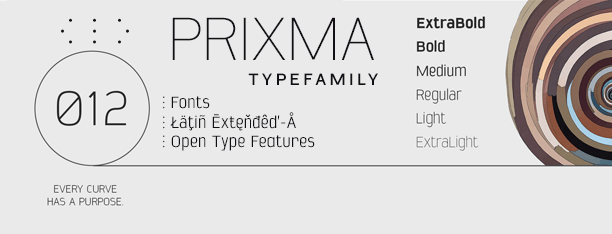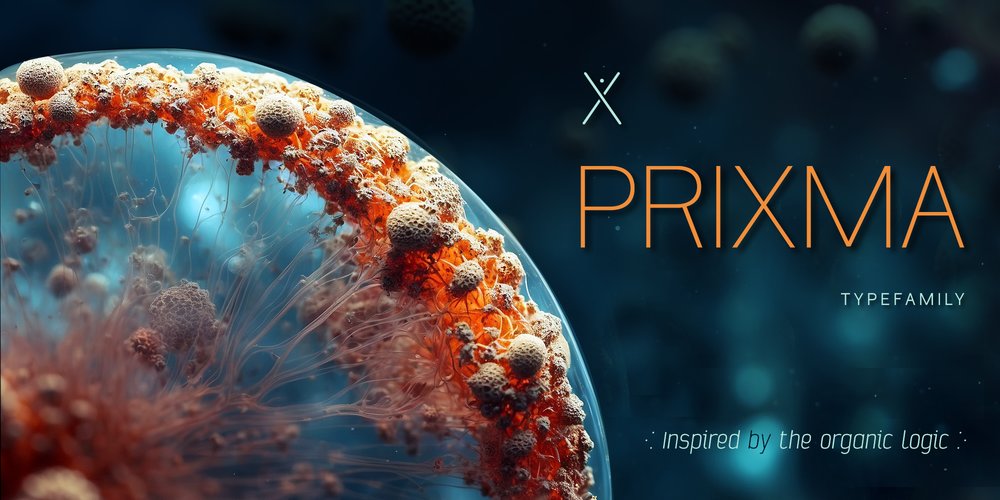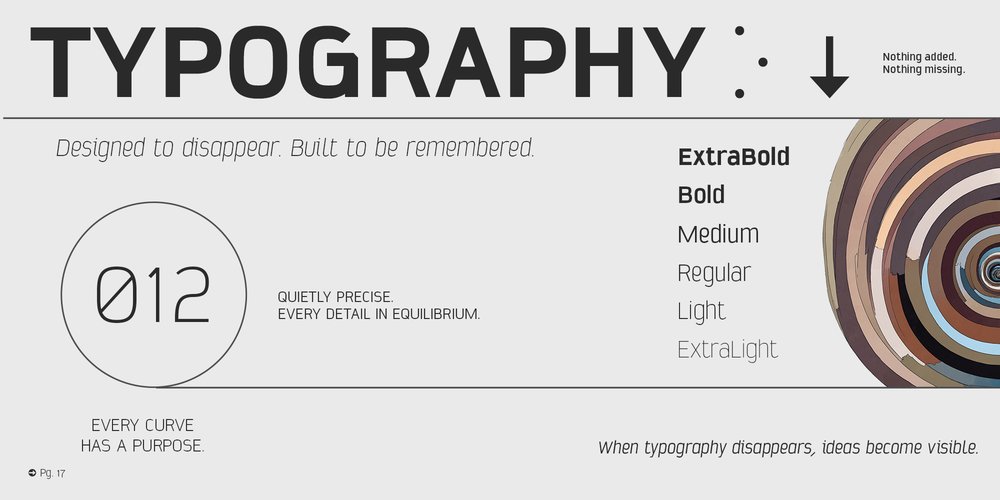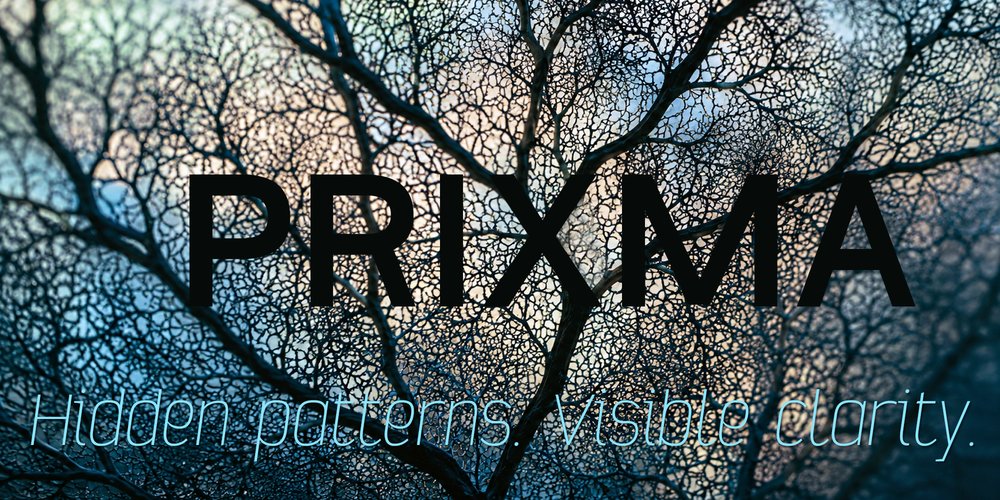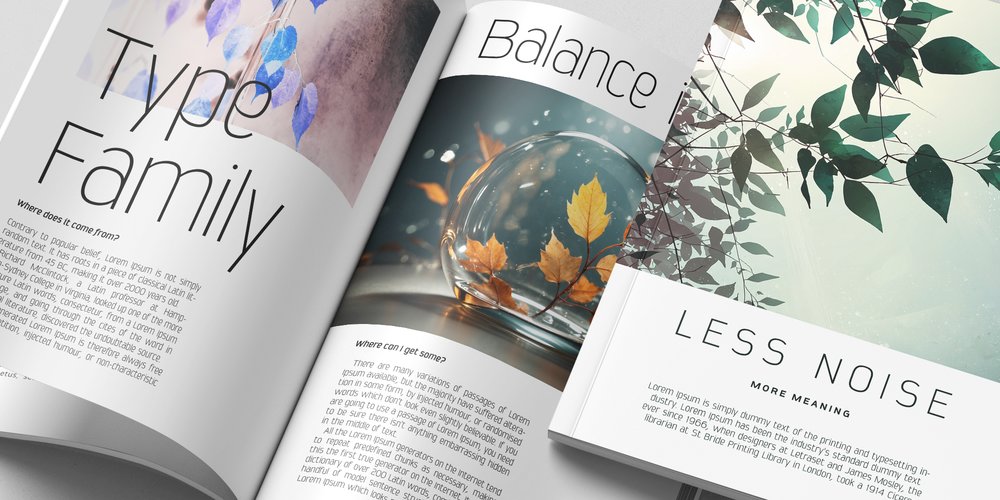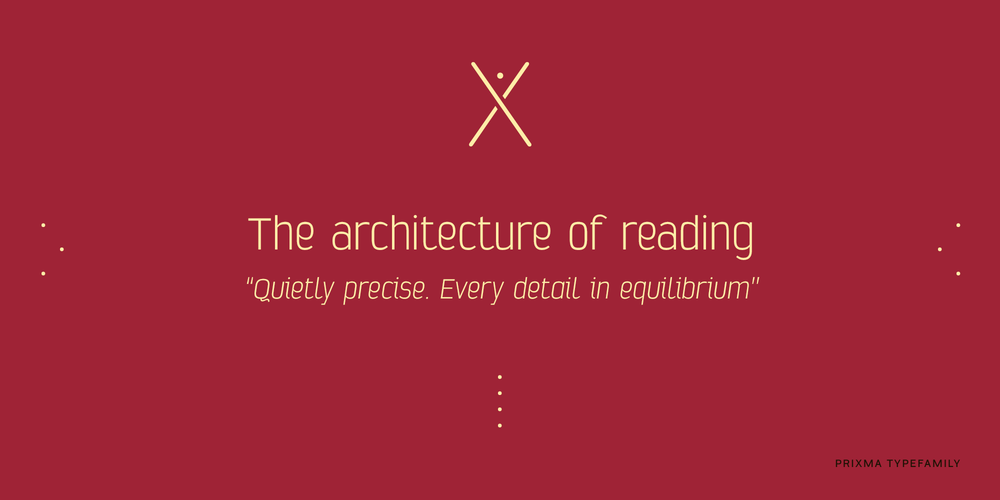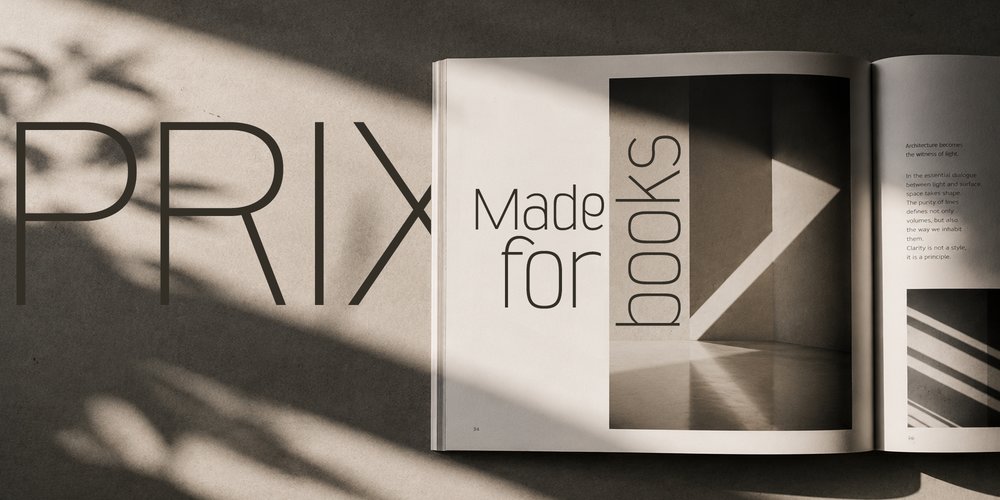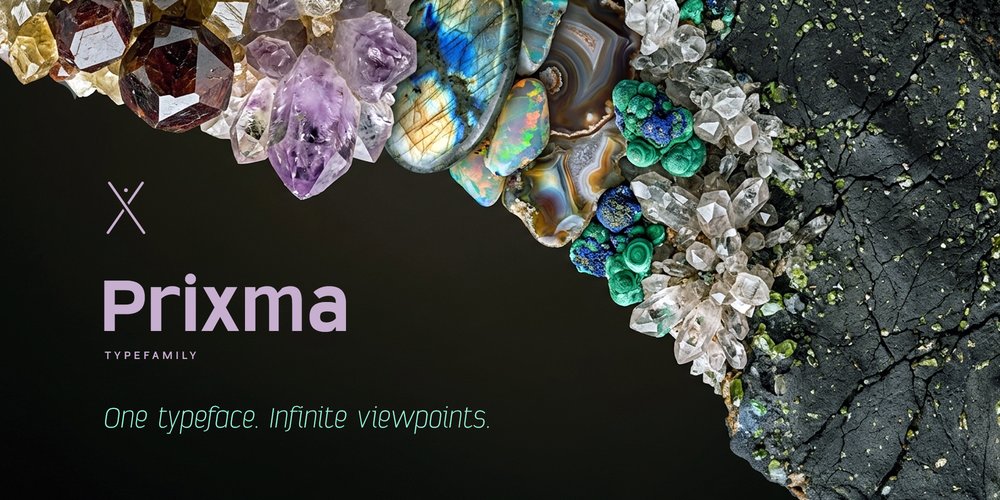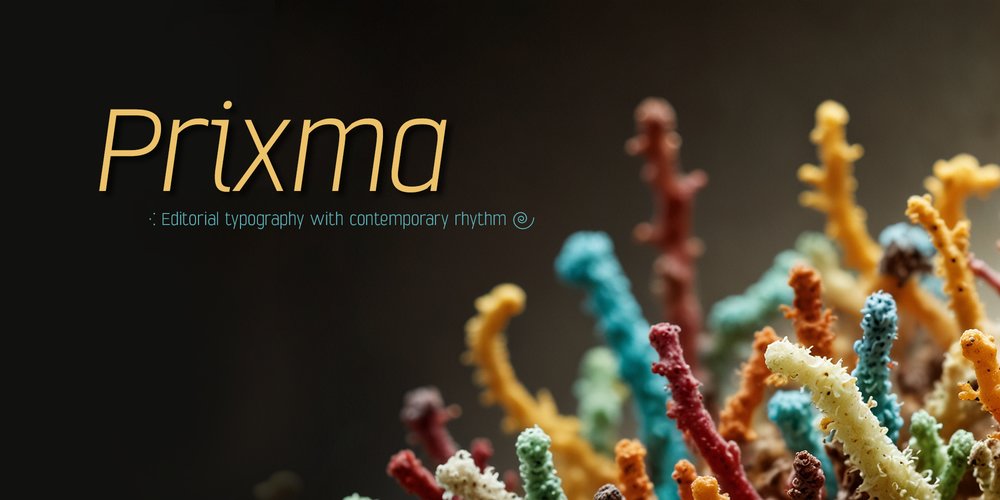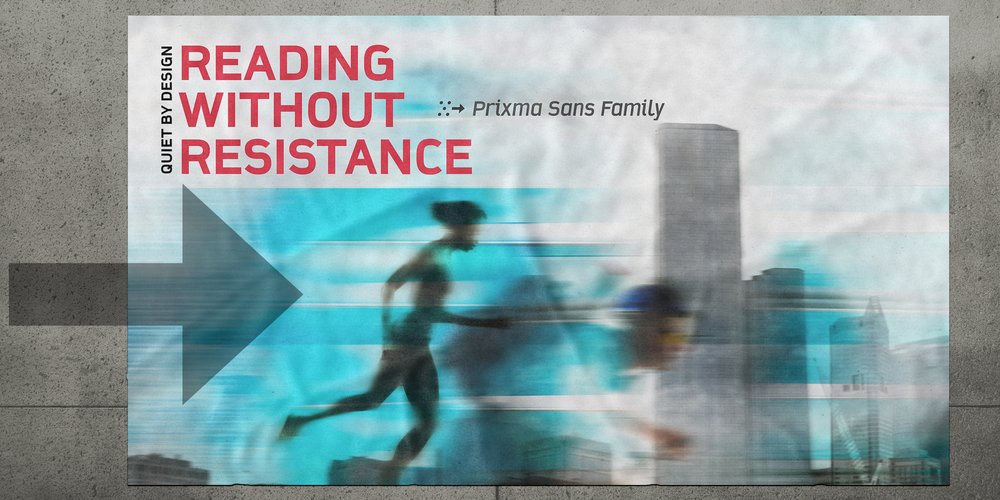
Estilo: Sans Serif, Editorial, Branding, Display, Packaging
Proporción: Extra Light, Light, Regular, Medium, Bold, Extra Bold
Alternates: 235
Latin-Extended: Latín Básico, Europa Occidental, Central & Oriental.
Funciones OpenType: Additional languages, All Alternates, Alternate Annotation Forms, Bitcoin, Capital Spacing, Contextual Alternates, Denominators, Discretionary Ligatures, Fractions, Historical Forms, Inferiors, Kerning, Localized Forms, Numerators, Oldstyle Figures, Optical Size, Ordinals, Scientific Inferiors, Slashed Zero, Standard Ligatures, Stylistic Set, Subscript, Superior letters, Superiors, Superscript.
Regular & Italic | 12 editorial fonts
Prixma es una familia tipográfica sans serif concebida para diseño editorial, identidad visual y sistemas de comunicación donde la claridad, la consistencia y la legibilidad son esenciales. Su construcción combina proporciones cuidadosamente equilibradas con un dibujo sereno y una textura uniforme que permanece estable desde los tamaños pequeños hasta los titulares.
Cada carácter ha sido refinado mediante un proceso continuo de ajustes ópticos, espaciado y kerning profesional, buscando un único objetivo: que la lectura fluya con naturalidad.
El resultado es una familia contemporánea, limpia y versátil, capaz de integrarse tanto en publicaciones editoriales como en proyectos de branding, diseño de información, interfaces, señalética o comunicación corporativa.
Prixma no persigue la neutralidad absoluta. Tiene personalidad. Simplemente ha decidido expresarla con discreción.
Una familia diseñada para trabajar
Disponible en los pesos Extra Light, Light, Regular, Medium, Bold y Extra Bold, junto con sus correspondientes versiones Italic, Prixma mantiene una voz coherente en toda la familia.
Su construcción homogénea facilita la combinación de pesos y estilos dentro de un mismo proyecto, ofreciendo una jerarquía clara sin perder continuidad visual.
Es una tipografía pensada para libros, revistas, informes, catálogos, identidad visual, packaging, publicaciones digitales y cualquier entorno donde el texto sea el verdadero protagonista.
Funciones OpenType
Prixma incorpora un amplio conjunto de funciones OpenType destinadas tanto al trabajo editorial como al diseño profesional.
La compatibilidad OpenType es completa para cualquier editor de texto:
- Ligaduras estándar y discrecionales.
- Oldstyle Figures
- Numeradores, denominadores e inferiores.
- Superíndices y Ordinales
- Fracciones automáticas.
- Amplio repertorio de signos y símbolos.
- Alternativas tipográficas para composición avanzada.
Estas funciones permiten construir documentos complejos manteniendo una composición limpia y consistente.
Latin Extended-A
Prixma ofrece compatibilidad completa con Latin Extended-A, incluyendo los caracteres necesarios para la mayoría de idiomas europeos occidentales y centrales.
Los diacríticos han sido dibujados específicamente para la familia, manteniendo el mismo criterio formal y el mismo equilibrio visual que el resto de caracteres.
Diseñada para desaparecer
Las mejores tipografías editoriales no interrumpen la lectura.
Organizan. Ordenan. Acompañan… después desaparecen.
Esa es precisamente la filosofía de Prixma.
Mirando hacia delante
Prixma nace como una familia abierta. Su arquitectura ha sido concebida para crecer con naturalidad mediante futuras incorporaciones, entre ellas variantes Slab Serif, Rounded o Small Caps que mantendrán el mismo lenguaje visual y la misma filosofía de diseño.